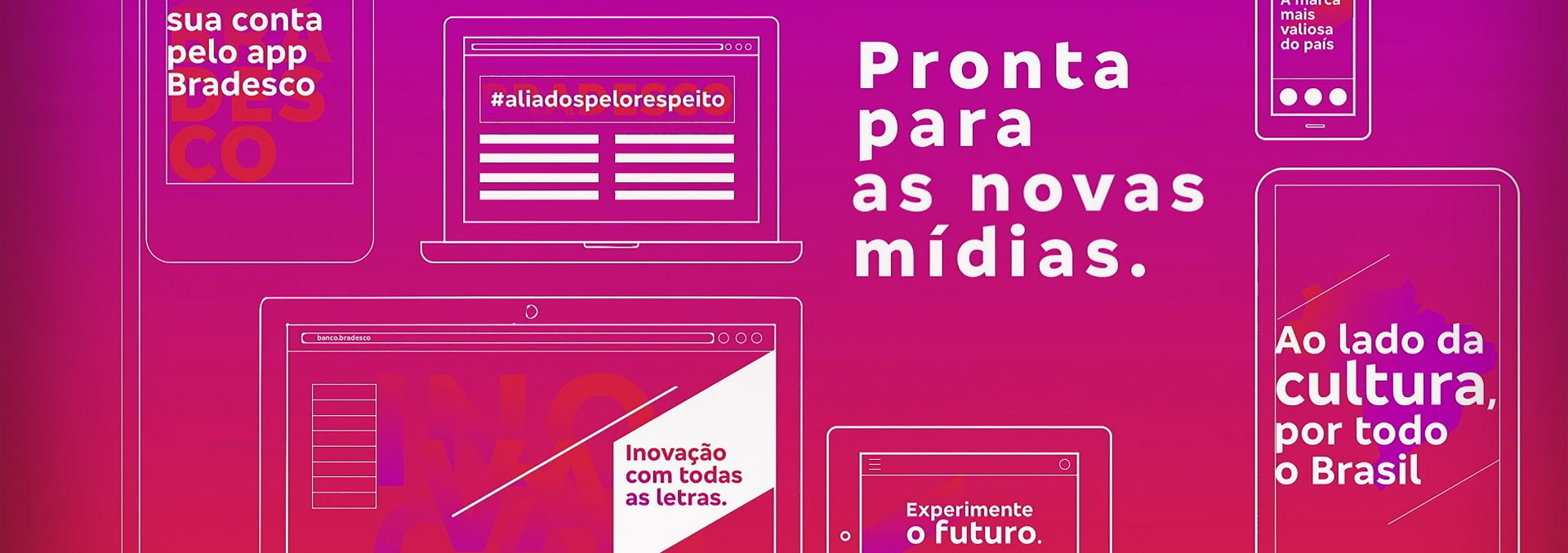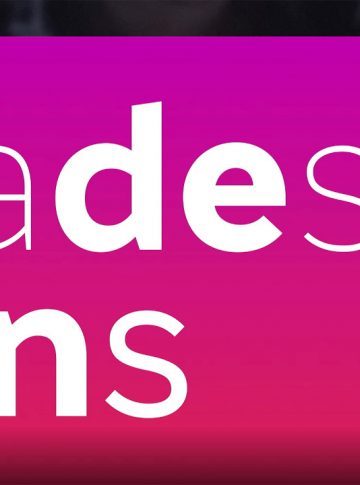
Bradesco lança sua própria tipografia chamada Bradesco Sans
Novidade traz detalhes sutis e que fazem alusão aos cortes diagonais característicos do design da nova logomarca
O Bradesco acaba de lançar sua tipografia proprietária, a Bradesco Sans. Após a última mudança realizada na logomarca do banco, que trouxe mais modernidade e maior aplicabilidade da marca para as novas mídias, a empresa agora aposta em uma tipografia própria.
A novidade reforça a identidade e o rejuvenescimento da marca e o processo contínuo de modernização no que diz respeito ao emprego de fontes.
Essa é a primeira vez que o banco lança uma fonte proprietária, que traz detalhes sutis e que fazem alusão aos cortes diagonais característicos do design da nova logomarca.
A criação da nova tipografia é de Fábio Haag, com coordenação da Epigram Superunion e o Design Team de Bradesco, junto com a Publicis, responsável pela comunicação institucional. No briefing para elaboração da fonte, a recomendação era criar uma tipografia baseada em dois pontos principais: que fosse funcional, de fácil leitura/legibilidade, atemporal e minimalista.
O processo de criação durou cerca de 7 meses. Foram apresentadas mais de 20 opções de fontes. Dessas, duas foram finalistas até se chegar à Bradesco Sans, que será implantada gradativamente pela instituição em todos materiais e canais.
O objetivo do Bradesco é que a nova fonte atenda à todas as necessidades de comunicação, com aplicabilidade para mídias diversas, mas também para o uso corporativo como por exemplo em formulários e sistemas.